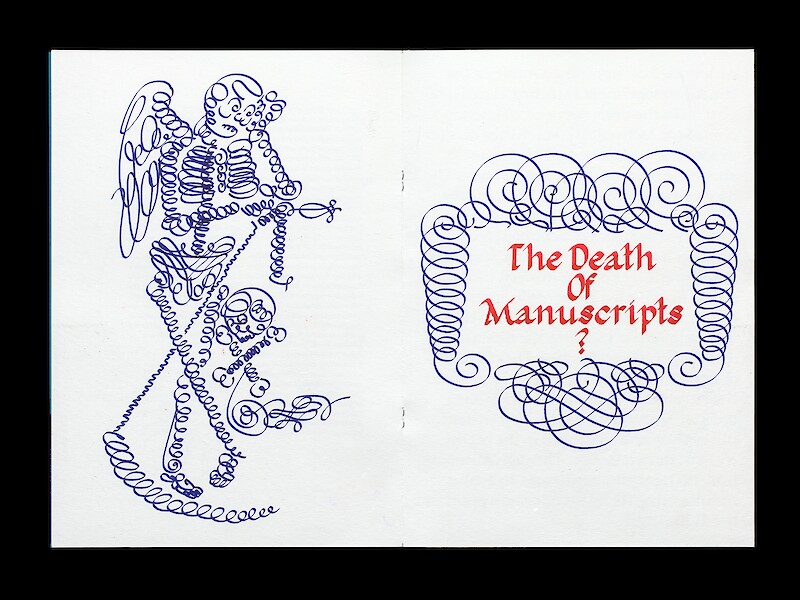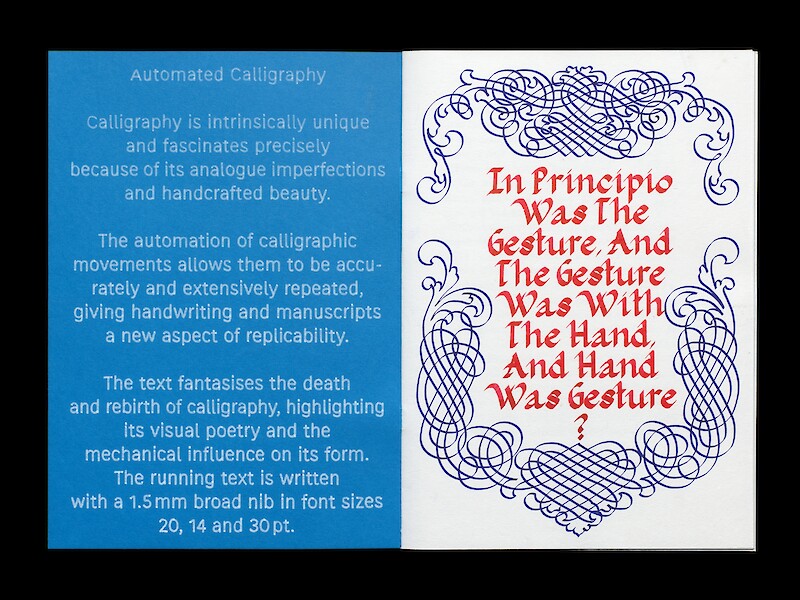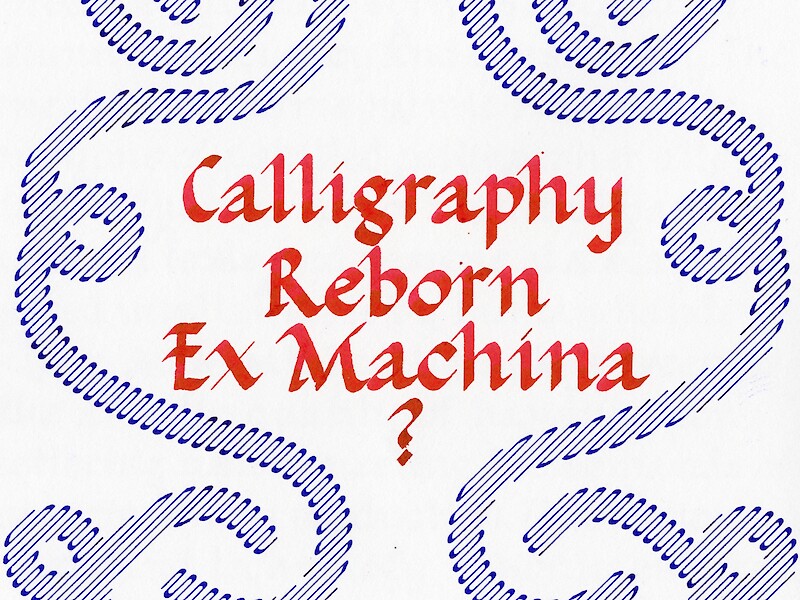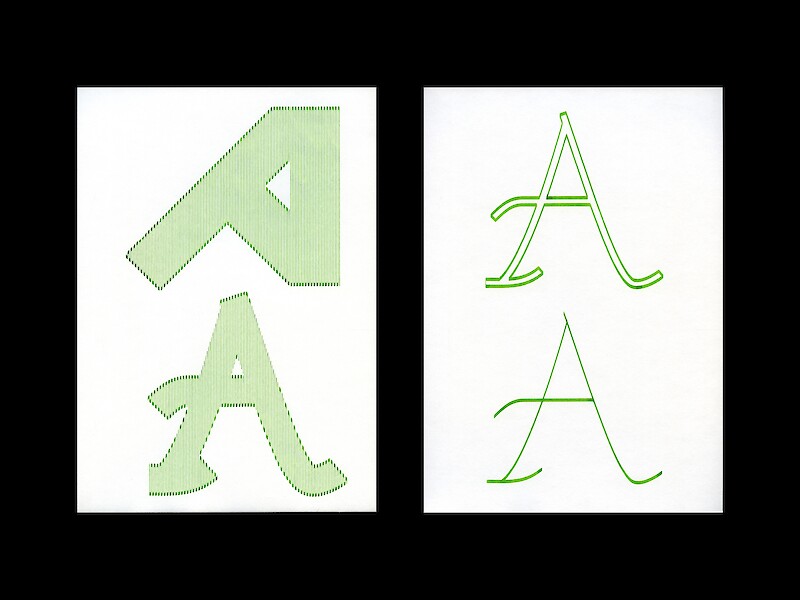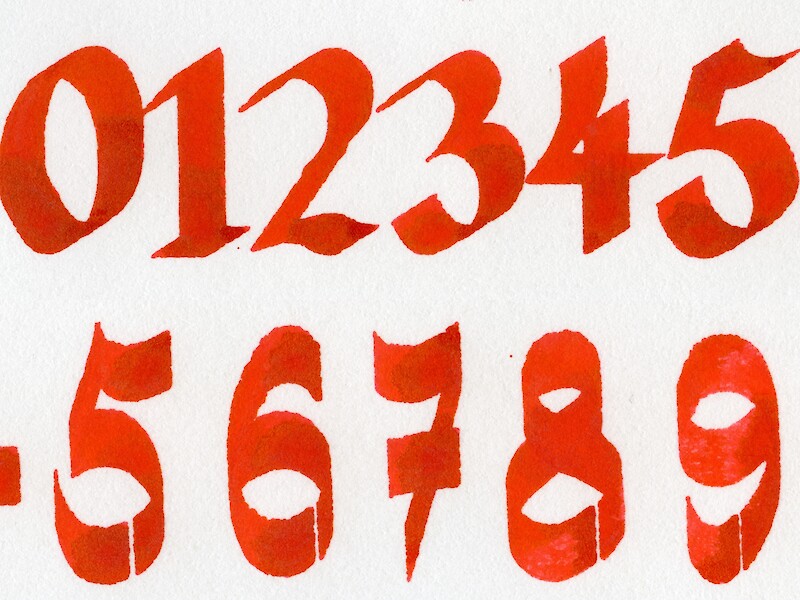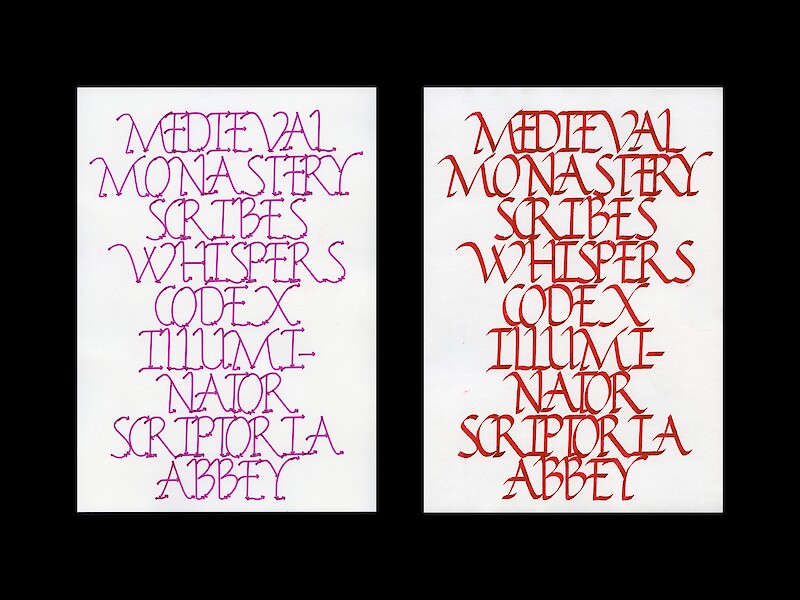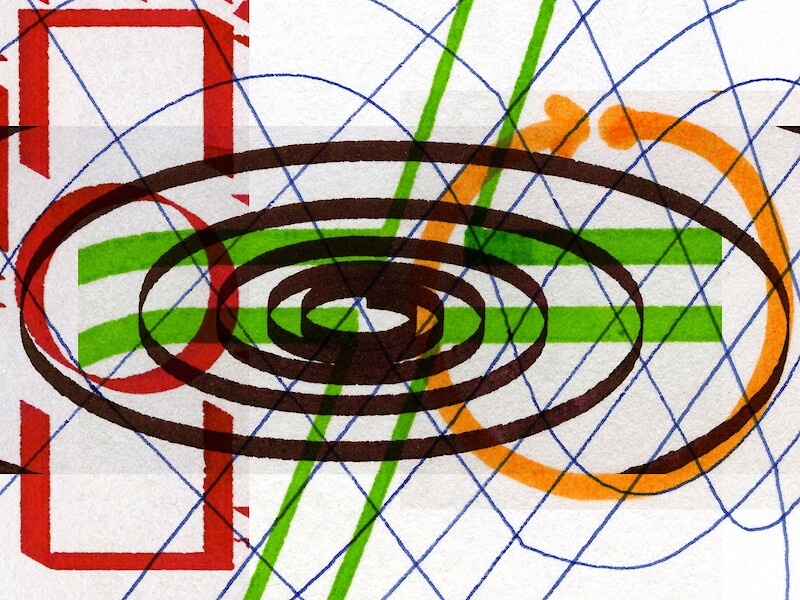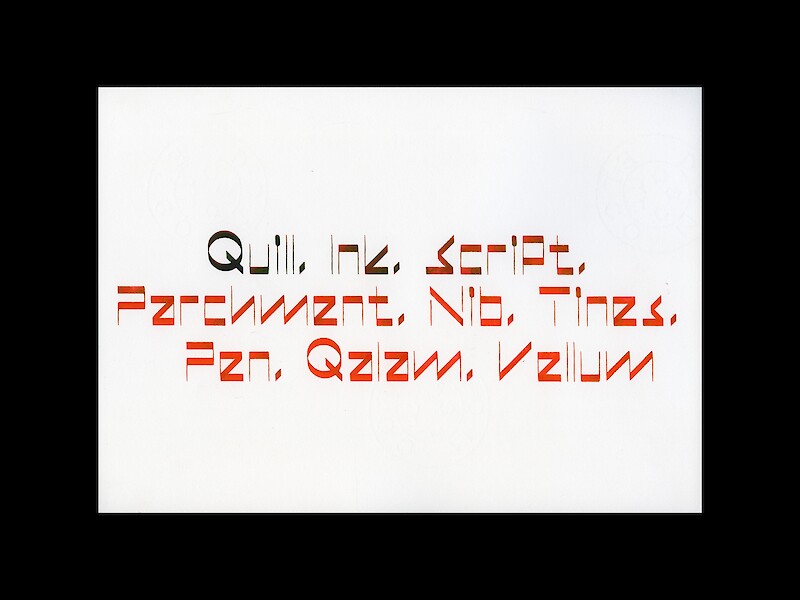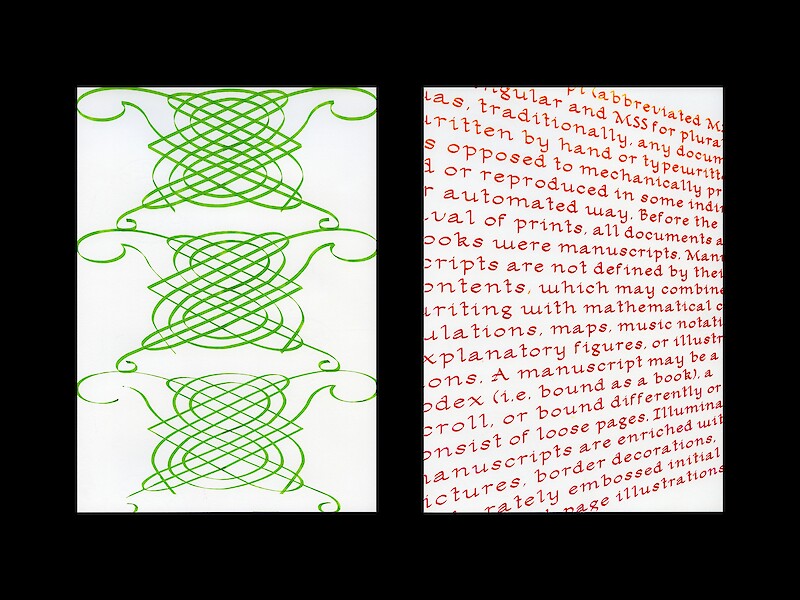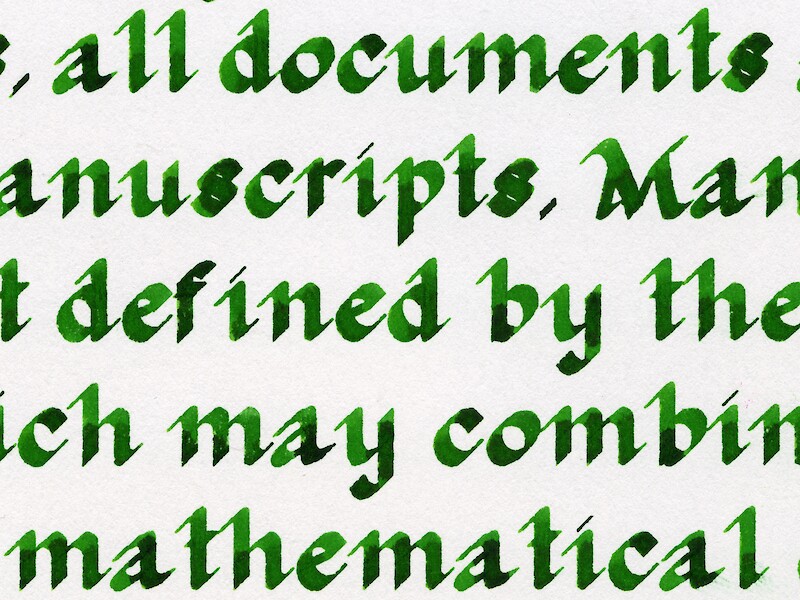
neo-Manuscripts
Die Zeiten des Manuskripts und handgeschriebenen Texts sind lang vorbei. Heutzutage drehen sich gestalterische Normen fast ausschliesslich um Druckerzeugnisse, so dass die manuelle Reproduktion von Texten völlig absurd erscheint. Auf halbem Weg zwischen althergebrachten Praktiken und zeitgenössischen Technologien stellt sich die Frage nach der automatisierten Kalligrafie, bei der manuelle Gesten durch mechanische ersetzt werden.
Die restriktive und langsame Methode, bei der ein CNC-Stiftplotter verwendet wird, um Texte zu reproduzieren, wirkt sich auf die Wahrnehmung von Büchern als Objekt oder als Behälter von Informationen aus. Sie beeinflusst die Vorstellung von Knappheit, Kostbarkeit und Zugänglichkeit. Diese formale Erkundung stellt den wahrgenommenen Wert des Buches in Frage und konfrontiert ältere Praktiken mit modernen Konventionen.